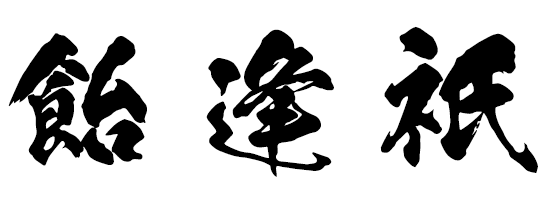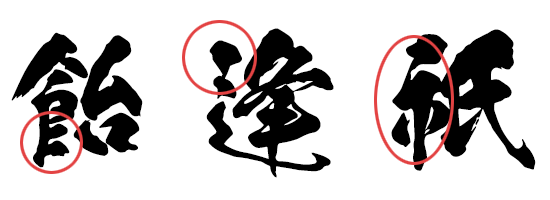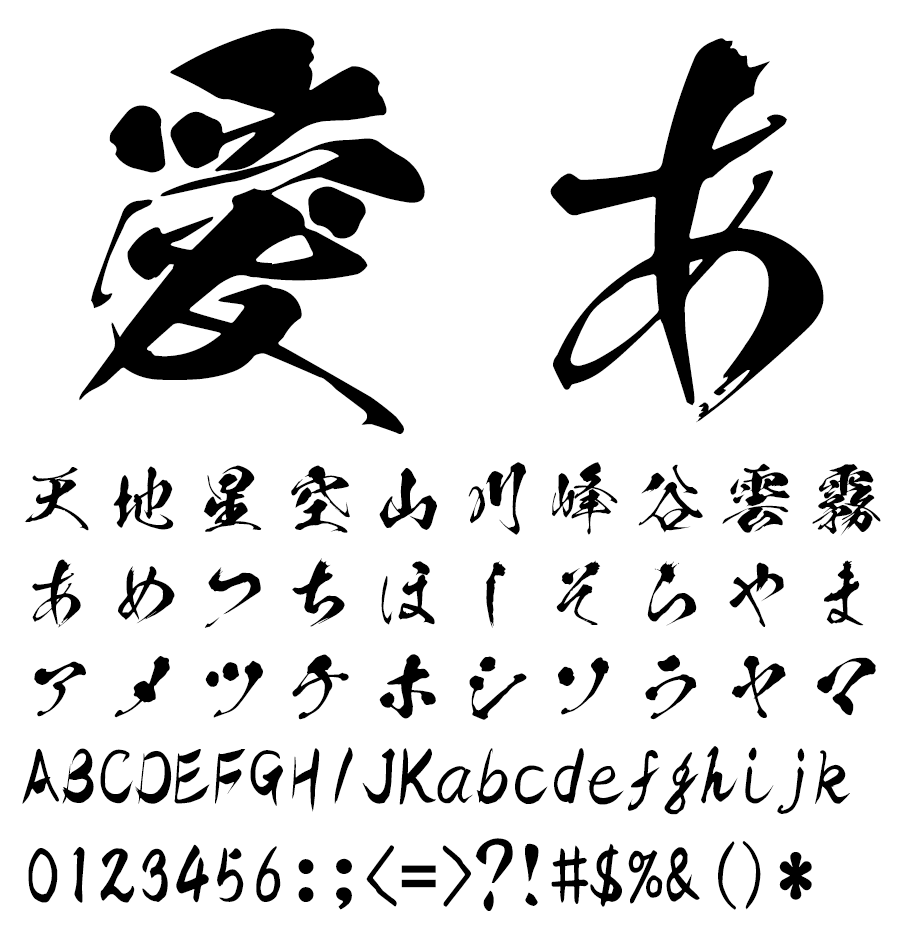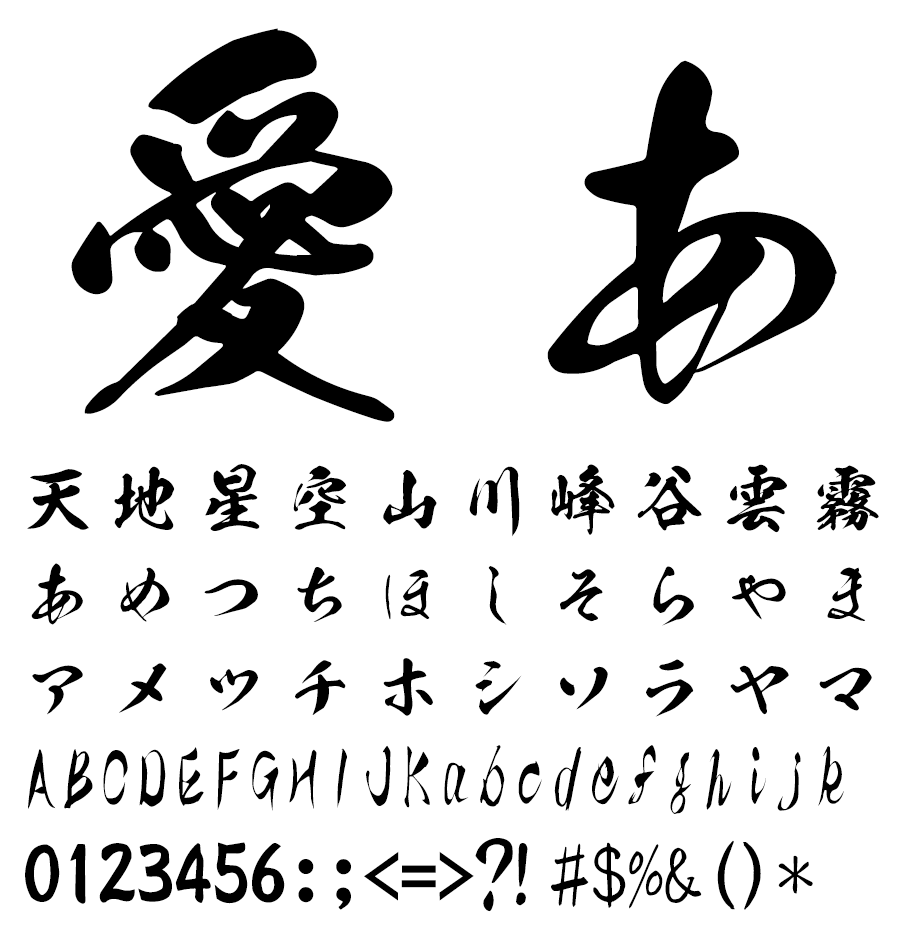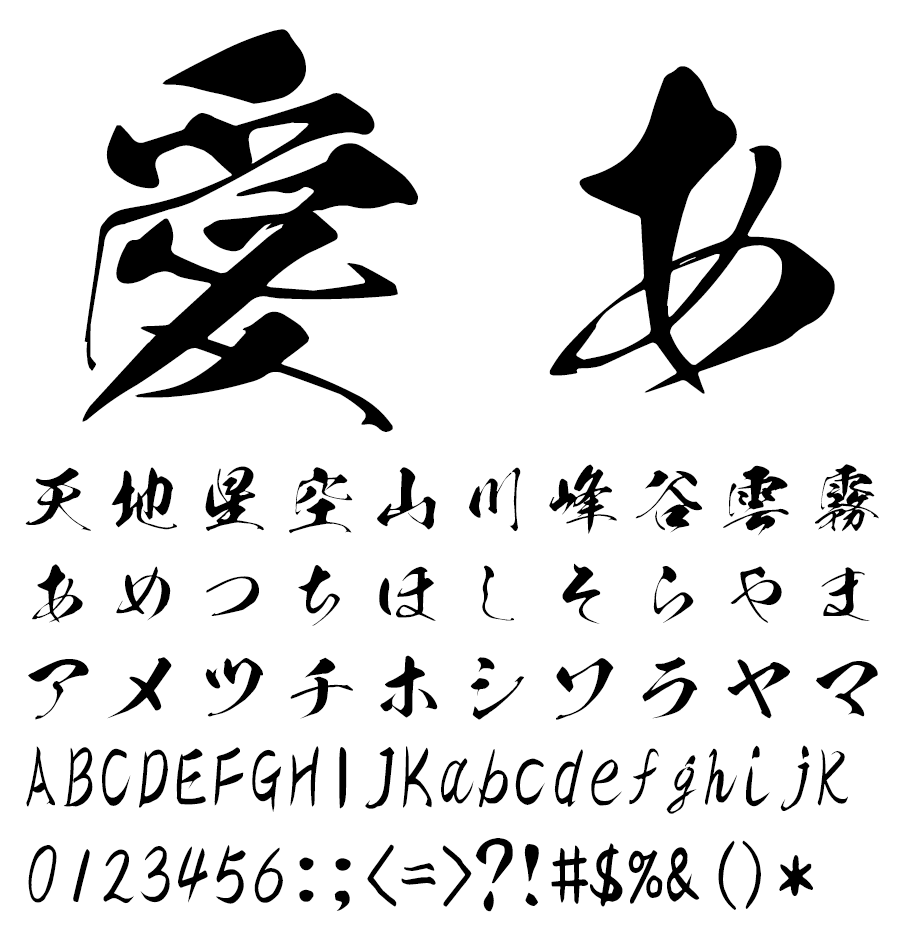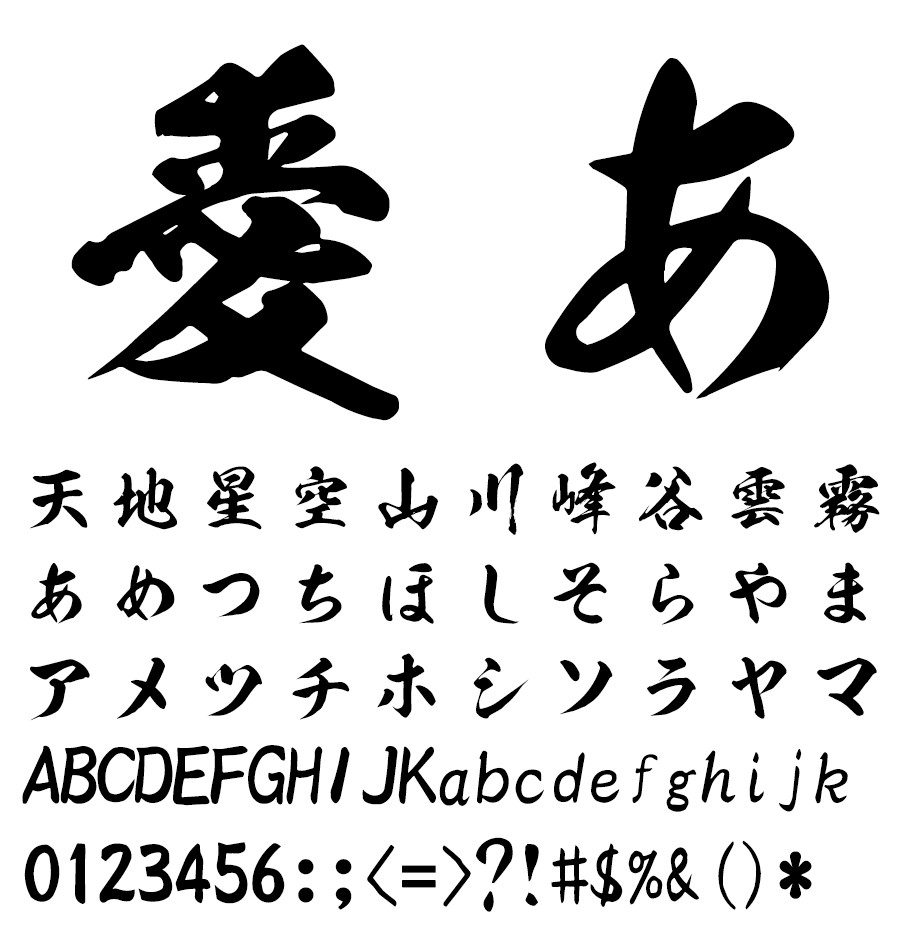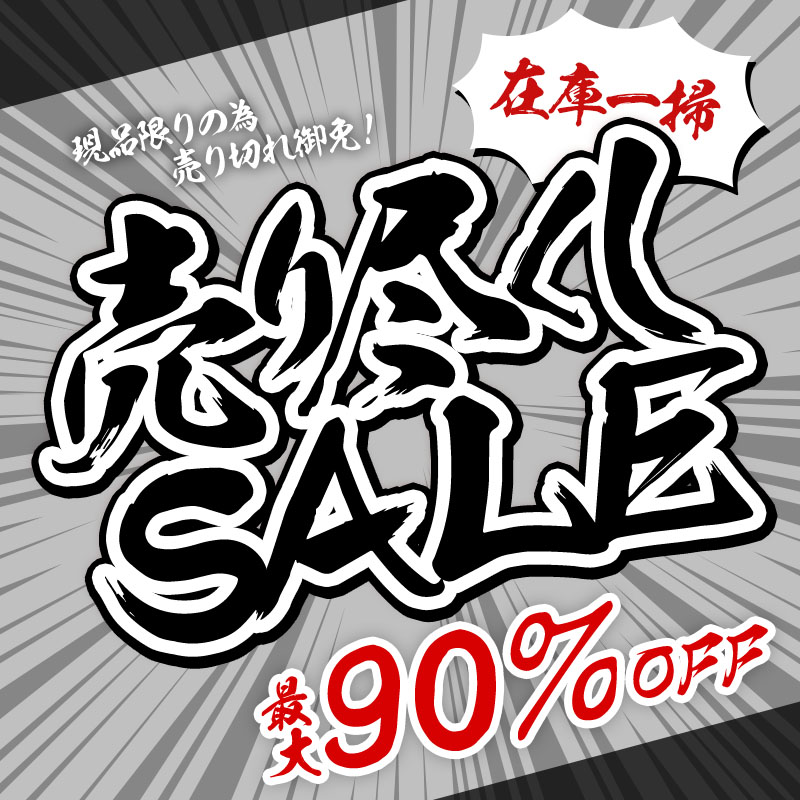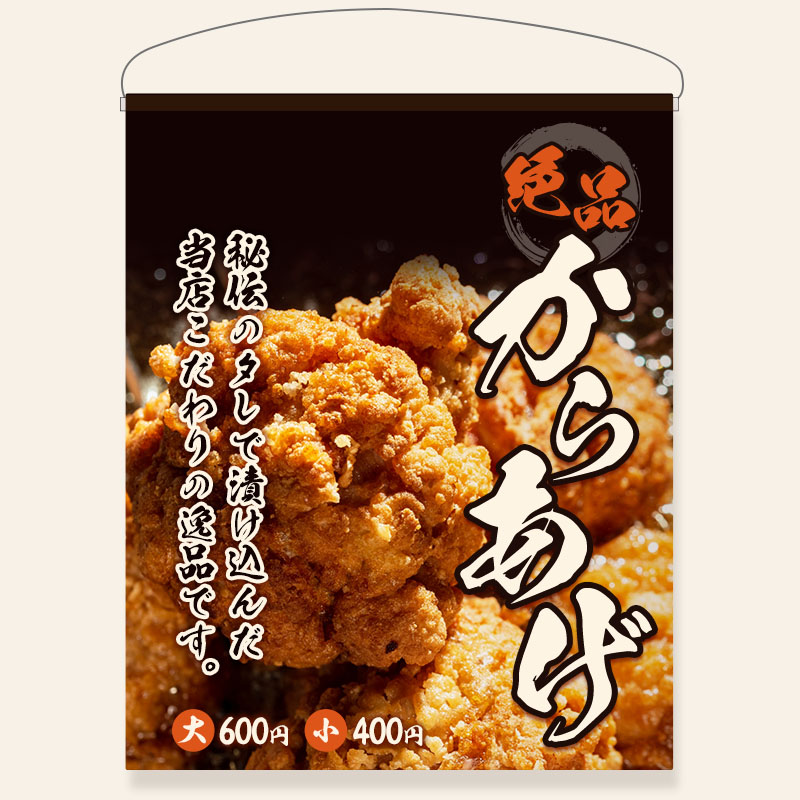
昭和書体が作り出す表情豊かな毛筆文字は、印刷物のみならず、ゲームやアニメの世界でも幅広く利用されており、デザイナーやクリエイターにとって欠かせない存在といっても過言ではありません。人気アニメ【鬼滅の刃】でも採用された注目の毛筆書体ブランドです。
爽シリーズは、従来の高解像度書体のかすれ等を適度に省略し、キレのあるシンプルなラインにリメイクしました。高解像度書体の1/3のデータ容量で、データが重くなりやすい動画やデジタルコンテンツに非常に使いやすくなっています。爽シリーズ全27書体のうち、「令明爽」×「バサころ爽」の2書体セットを、2024年2月29日までの期間限定・標準価格の84%OFFとなる特別価格3,300円(税込)でご提供します。
本格毛筆書体ブランド  昭和書体 とは?
昭和書体は、あらゆる使用目的にマッチする毛筆書体の提供を目指し、揮毫職人が1文字1文字丁寧に書き上げた本格毛筆書体ブランドです。
1950年頃から広告媒体製造業としての取組みを起源とし、2006年に毛筆フォント制作会社としてコーエーサインワークスを設立。2013年の組織変更を経て株式会社昭和書体に社名変更されました。直筆と見間違えるようなPC用毛筆書体制作にこだわりを持って、自社内ですべての制作業務を行い、和文毛筆という文化の継承に取り組んでいます。
昭和書体の特徴
書家「綱紀栄泉」が1文字1文字丁寧に書き上げた筆文字
昭和書体の多くの書体を手掛けてきた書家「綱紀栄泉 (つなのりえいせん)」。1人の書家が64種類もの形態の異なる毛筆書体を書き上げた例を他に見たことがありません。1つの書体には第一水準から第二水準までの約7,000文字が必要で、64書体に書き分けた文字は約50万字。書き直しを含めると2倍近くにものぼる気の遠くなる作業です。まさに奇人であり天才と言う他なく、現代の弘法大師と呼べる存在です。奇しくも紫雲山上宮寺 (しうんざんじょうぐうじ) という寺の長男として生まれている事も、何らかの仏縁を感じざるを得ません。昭和10年生まれの高齢ながら精力的に活動されていましたが、2022年3月惜しまれながらも他界されました。
現在は御子息の坂口茂樹氏が二代目栄泉としてその遺志を引き継ぎ、鋭意揮毫中です。
現代の弘法大師とも言える昭和書体の書家「綱紀栄泉」
書家「綱紀栄泉 (初代)」
昭和書体 爽シリーズとは?
カッティングシートや高負荷処理に適した「シンプルライン」
爽シリーズとは、『昭和書体』高解像度書体シリーズのカスレを少なく調整し、容量を小さくする事でカッティングや動画などに使用しやすくしたキレのあるシンプルなラインが特徴のフォントシリーズです。従来の高解像度書体と比べ、およそ3分の1のデータ容量になっています。
高解像度シリーズと比べるとカスレが減り迫力は抑え気味ですが、データが重くなりやすい動画やデジタルコンテンツに非常に使いやすくなっています。印刷やタイトルなど目立たせたい場合はより直筆に近い高解像度シリーズ、小さな文字で読ませたい場合などは爽シリーズと、用途に応じた使い分けを推奨いたします。
「闘龍」のデザインとそのアウトライン
「闘龍爽」のデザインとそのアウトライン
爽シリーズの魅力 JIS90/JIS2004が選べる
ほとんどの昭和書体フォントでは、従来から広く利用されてきたJIS90規格のフォントの他、近年主流となりつつあるJIS2004規格のフォントもラインナップされています。日本語フォントを開発する複数のメーカーで採用されている慣例と同じく、昭和書体でも、JIS2004規格に準じたフォント名の末尾には"N"の文字を付与しています。
両規格では漢字のうち168字の例示字形が若干異なっており、概ねJIS90字形のほうが略字風、JIS2004字形のほうは正字・旧字風のデザインになっています。
JIS90/JIS2004で字形が異なる文字の例
JIS90字形
例: 闘龍爽
JIS2004字形
例: 闘龍爽N
NなしとN付きの字形差 (JIS90・JIS2004で例示字形が異なる文字の一覧)
JIS90規格とJIS2004規格で例示字形が異なる168文字のうち、シリーズ収録範囲に含まれる167文字を「闘龍爽」「闘龍爽N」で比較した一覧です。
(毛筆書体の特性上、明朝体やゴシック体ほどには字形差がはっきりしない文字もあります。)
文字サンプル
令明爽
バサころ爽
使用例
令明爽・バサころ爽
仙人爽・寿鶴爽・黒龍爽
飛龍爽・銀龍爽・朱雀爽